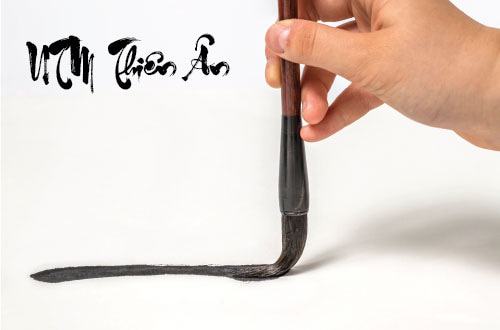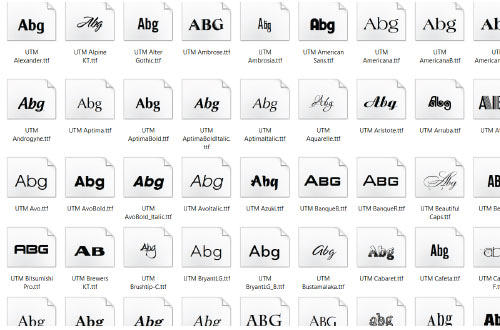
Bạn đang tìm kiếm một kho tàng của các font chữ đẹp và đa dạng để làm cho thiết kế của bạn trở nên nổi bật và chuyên nghiệp? Đừng bỏ lỡ cơ hội tải về bộ Font UTM - một bộ font chữ Unicode được Việt hóa chuyên nghiệp, hỗ trợ việc gõ tiếng Việt một cách dễ dàng. Font UTM cung cấp cho bạn không chỉ một loạt các font chữ độc đáo mà còn nhiều tính năng hấp dẫn khác.
Giới thiệu font UTM
Trọn bộ font chữ utm việt hóa
UTM Font là viết tắt của bộ Unicode Thiên Minh - một bộ font chữ Việt hóa được phát triển bởi nhóm Thiên Minh Font. Bộ font này bao gồm hơn 100 font chữ với nhiều phong cách khác nhau, từ hiện đại đến cổ điển, từ thanh lịch đến mạnh mẽ.
Các font chữ UTM đều được thiết kế theo tiêu chuẩn Unicode, đảm bảo khả năng tương thích với tất cả các trình duyệt web và hệ điều hành.
Những ưu điểm nổi bật của font UTM
Font chữ sans-serif hiện đại, thanh lịch, phù hợp cho các thiết kế website, logo, poster,...
Font UTM không chỉ đẹp mắt mà còn cung cấp một loạt các lợi ích đáng kể:
• Đa dạng phong cách: Các font chữ UTM có thể đáp ứng mọi nhu cầu thiết kế, từ thiết kế website, thiết kế đồ họa, đến thiết kế in ấn.
• Đẹp mắt, dễ đọc: Các font chữ UTM được thiết kế với đường nét tinh tế, rõ ràng, giúp người dùng dễ dàng đọc và hiểu nội dung.
• Tương thích cao: Các font chữ UTM đều được thiết kế theo tiêu chuẩn Unicode, đảm bảo khả năng tương thích với tất cả các trình duyệt web và hệ điều hành
Các font chữ UTM phổ biến
Dưới đây là một số font chữ UTM phổ biến:
• UTM Avo: Font chữ sans-serif hiện đại, thanh lịch, phù hợp cho các thiết kế website, logo, poster,...
• UTM Traijan Pro: Font chữ sans-serif mạnh mẽ, cá tính, phù hợp cho các thiết kế website, đồ họa,...
• UTM Avenida: Font chữ sans-serif cổ điển, sang trọng, phù hợp cho các thiết kế website, in ấn,...
• UTM Mabella: Font chữ script thanh lịch, lãng mạn, phù hợp cho các thiết kế website, đồ họa,...
Cách sử dụng font chữ UTM
Font UTM thư pháp việt hóa.
Kết luận
Font chữ UTM là một bộ font chữ Việt hóa đẹp mắt, dễ đọc và đa dạng phong cách. Bộ font chữ này sẽ giúp website của bạn trở nên chuyên nghiệp và thu hút hơn.